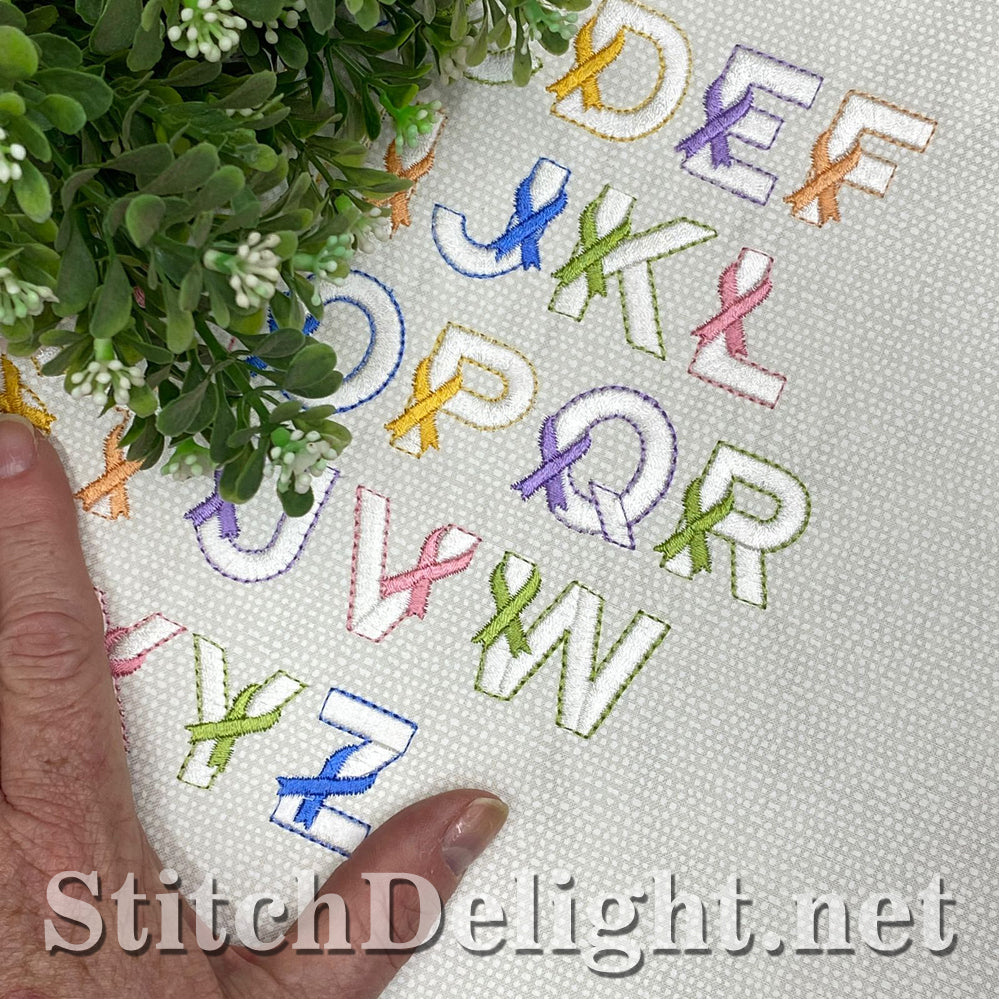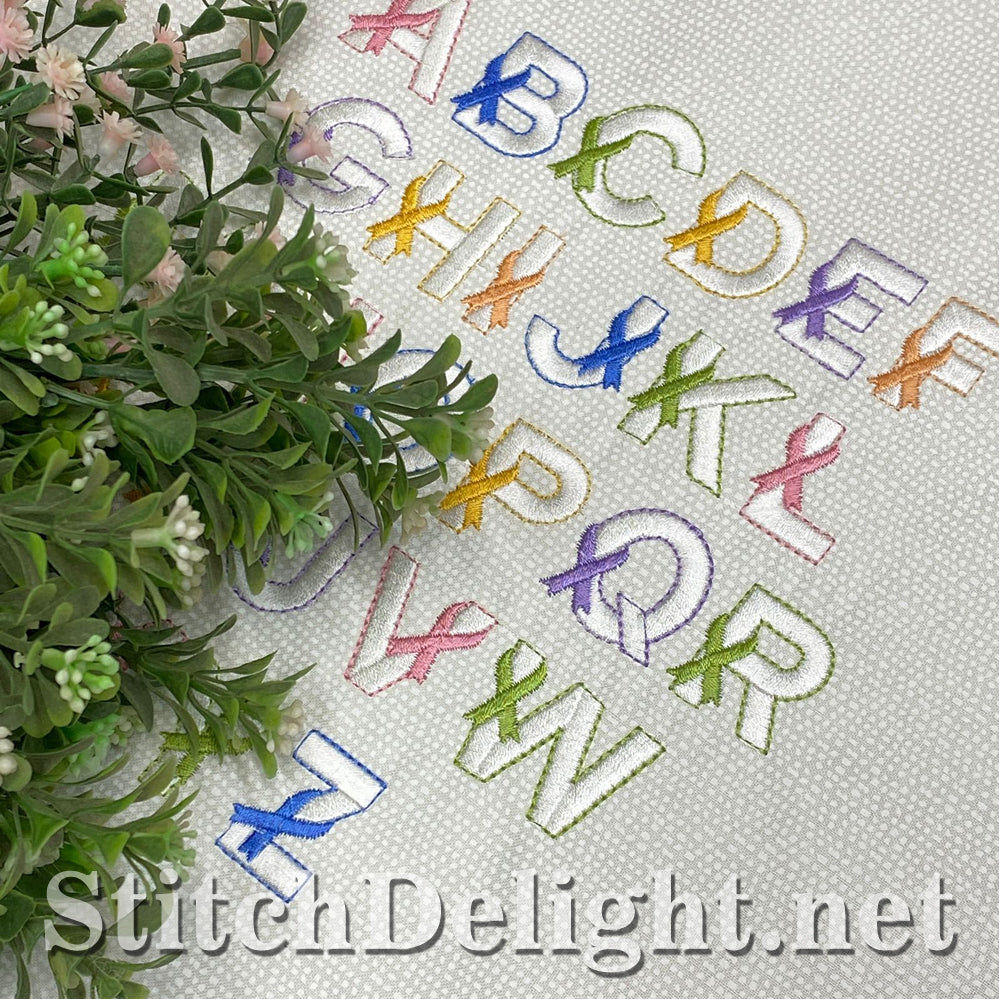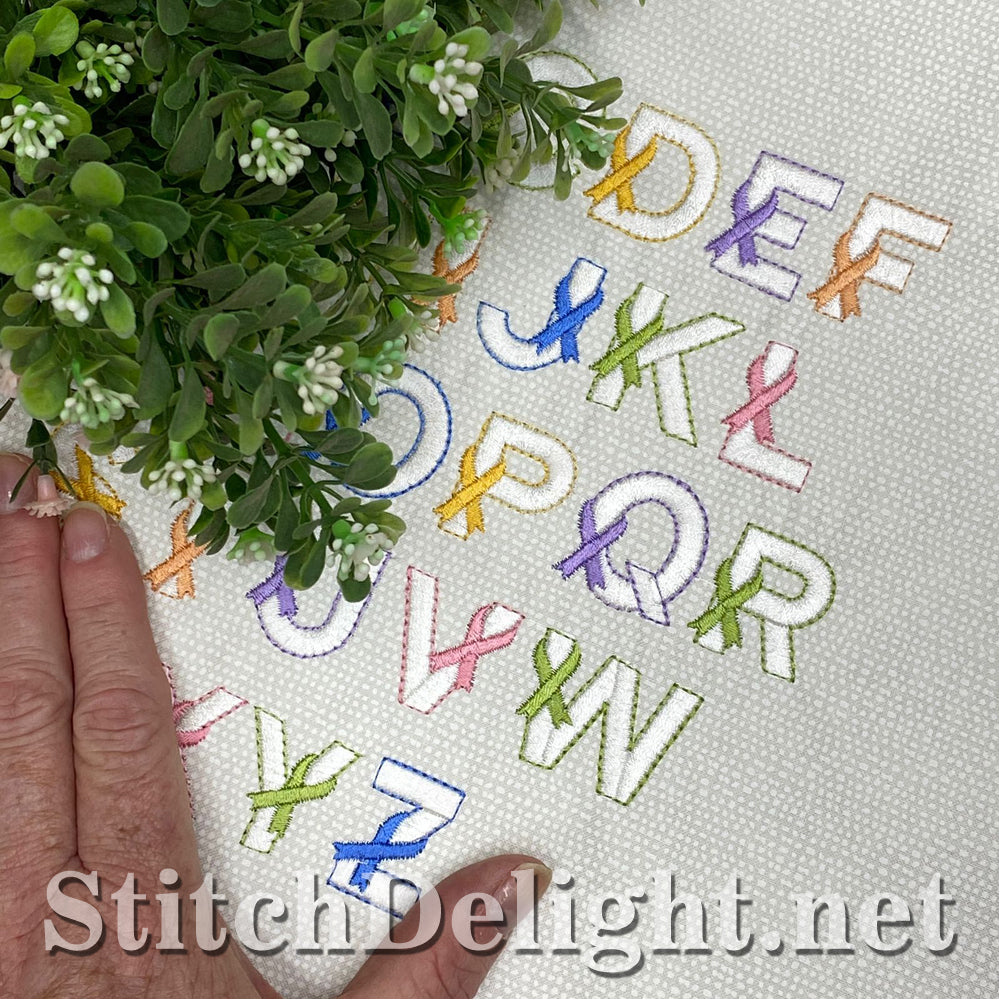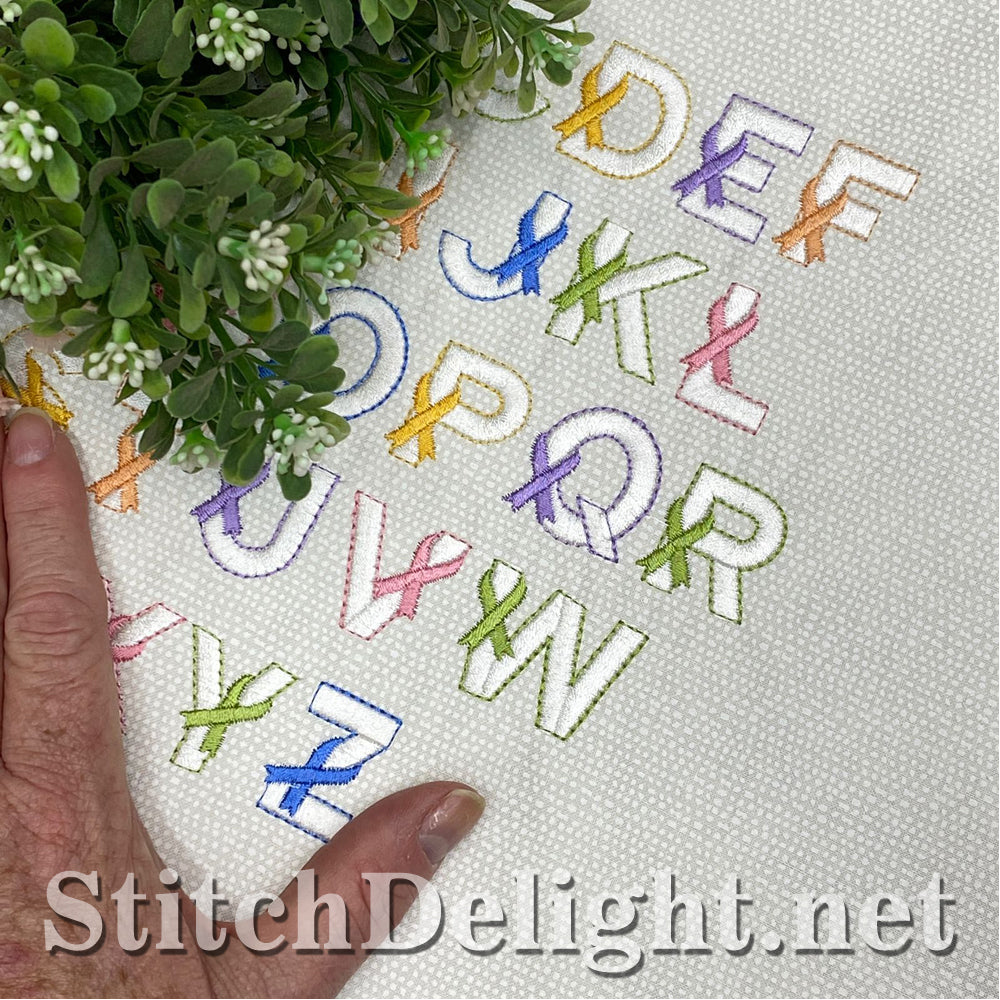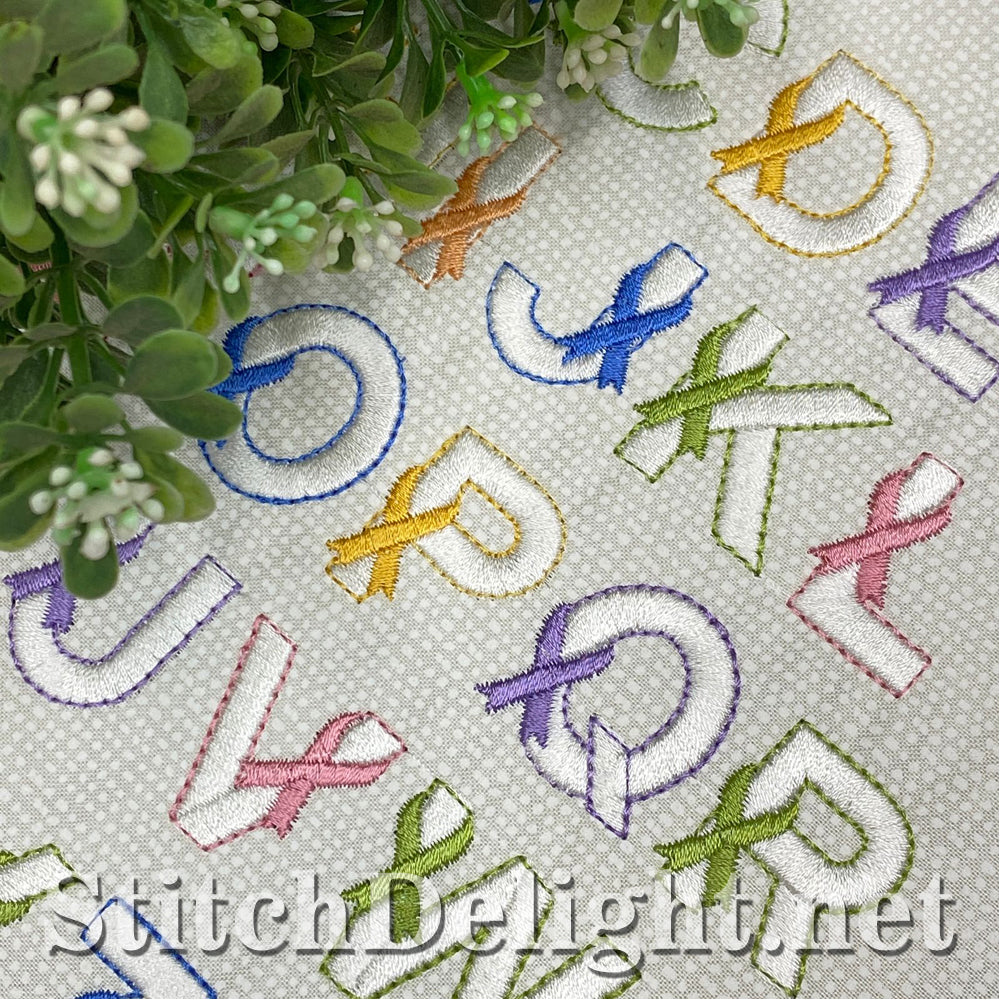
La police cancer est conçue pour le cerceau 4x4 et a une hauteur moyenne de seulement 1", ce qui la rend idéale pour la couture de vêtements ou sur des cadeaux.